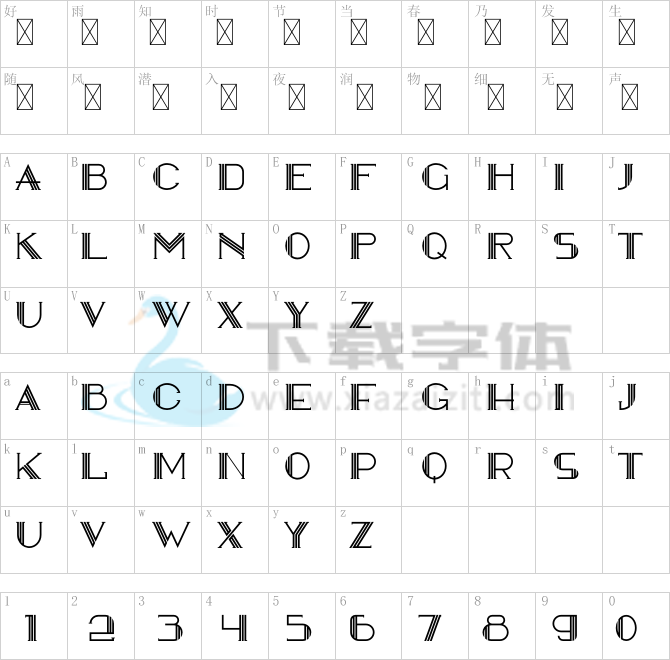
AVENIDA.otf字体下载,这款字体结构工整、笔画清晰,兼顾美观与易读性,适用于标题、正文、海报、包装、LOGO 等多种场景。字形优雅稳定,风格百搭耐看,适配日常排版与创意设计,让文字呈现更舒适、更具质感。AVENIDA.otf字体下载一笔一画,皆是细节,以均衡的比例、流畅的线条打造舒适视觉体验,字形端正大气,风格简约现代。无论是商业设计、品牌宣传还是日常排版,都能轻松驾驭,让文字更有格调与力量。AVENIDA.otf字体下载字体下载。